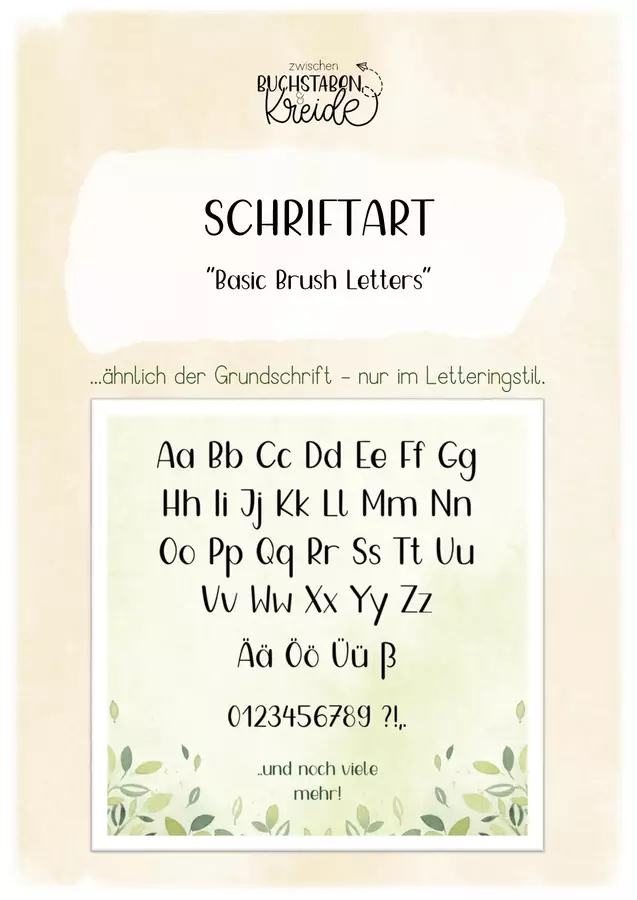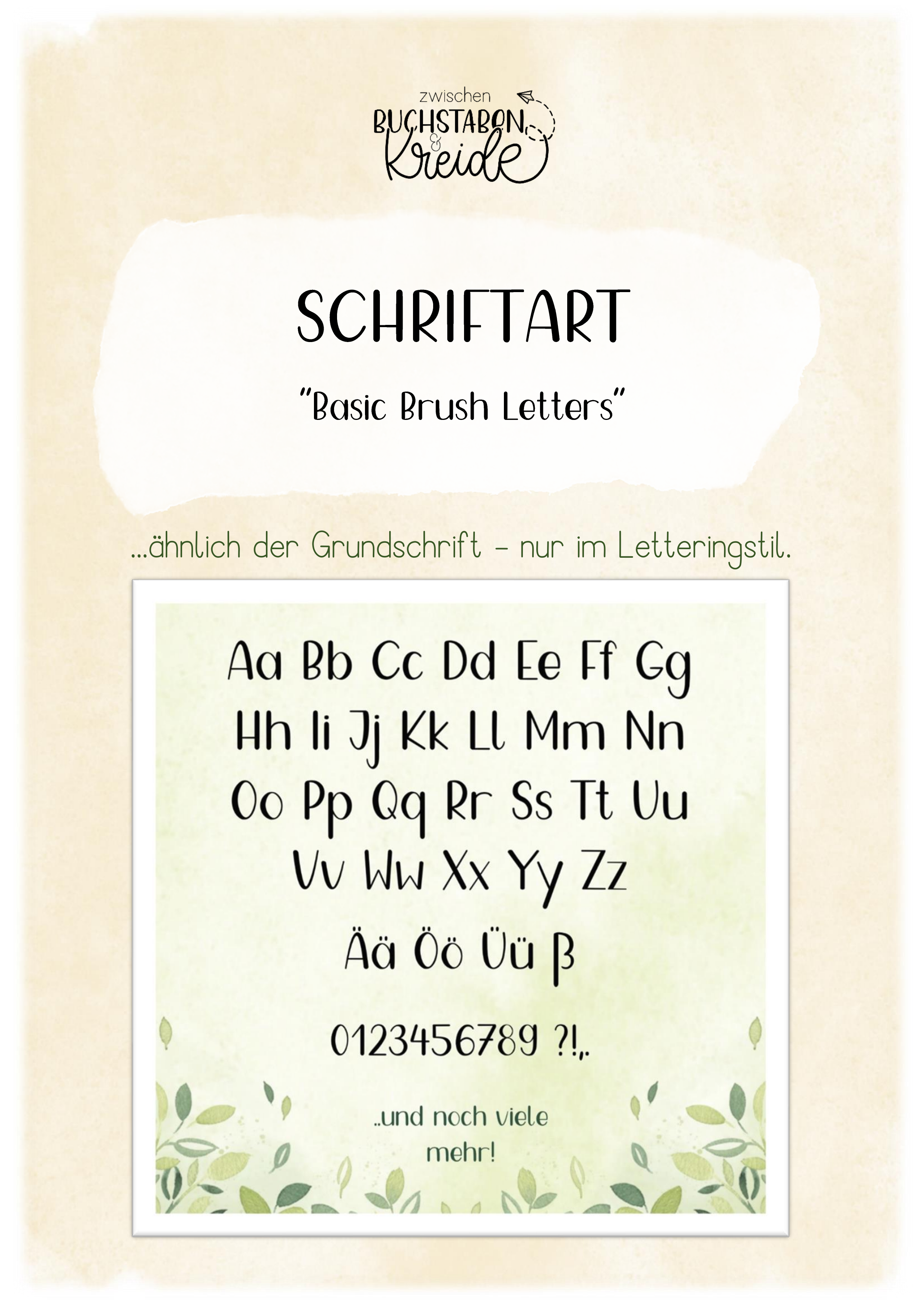
Die Schrift ist ein Update zu "Capitallettering" von mir, die ich in meinen bisher veröffentlichten Materialien verwendet habe (die aber nicht zum Verkauf stand).
Sie ist der Grundschrift absichtlich sehr ähnlich, sodass sie auch von den Jüngsten gut gelesen werden kann.
Schriftart "Basic Brush Letters"